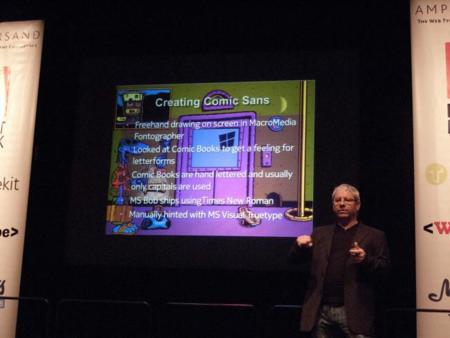
Si hay una tipografía que despierta pasiones (tanto para bien como para mal) y de la que se abusa, esa es la Comic Sans. Y aunque viene instalada por defecto en todas las versiones de Windows desde que tengo memoria, su objetivo era bastante distinto. Según cuenta Vincent Connare, su creador, esa tipografía fue creada para acompañar un proyecto fallido de Microsoft.
El nombre que tenía era Microsoft Bob y era una interfaz para niños que funcionaba por encima de Windows 3.1. Su mascota, que podía ser seleccionada por el usuario, hablaba por medio de bocadillos. Y no quedaba del todo bien que este perro hablara con Times New Roman, Garamond o Arial. Microsoft quería esta fuente fuera más parecida a la de un cómic, y le encomendaron la tarea a Connare. El resultado fue Comic Sans.
Aunque el problema era que tenía que hacerse muy rápido dado que Microsoft Bob iba a ser lanzado inminentemente (y de hecho no llegó a lanzarse con ella, apareciendo los mensajes con Times New Roman). De modo que lo que hizo Connare fue dibujar los caracteres con su propio ratón, para que fueran más "redondeados". Tardó un total de tres días, y dice que sabía exactamente lo que quería. Podríamos decir que fue "a tiro hecho", tras documentarse utilizando cómics.
Y, aunque Microsoft Bob no triunfó (de hecho el proyecto fue cancelado sin muchos miramientos), Comic Sans sí que ha perdurado en el tiempo, sobre todo por destacar por encima de las demás fuentes, que perfectamente podrían ser utilizadas en libros.
De hecho gusta tanto a los usuarios de Windows que, como todos sabéis y habréis visto alguna vez, es usada constantemente, incluso en contextos en los que no es en absoluto apropiada (he llegado a ver exámenes de universidad con esa tipografía, y es famosa la imagen de la lápida en Comic Sans). Y son famosas campañas en su contra como Ban Comic Sans.
Sea lo que sea, estoy seguro de algo: vamos a tener Comic Sans por mucho tiempo.